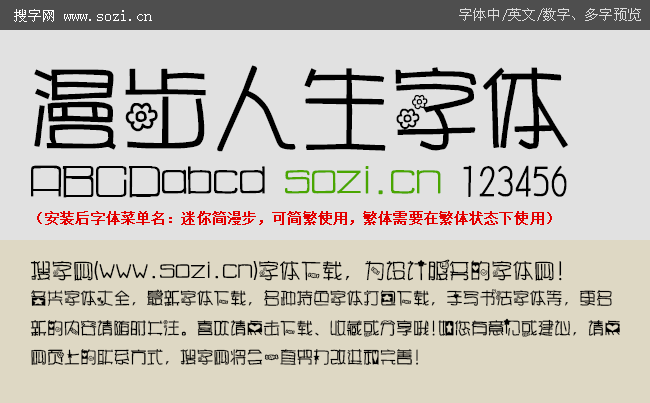
漫步人生字體
搜字網(wǎng)給大家提供一款漫步人生字體手機(jī)中文字體下載。這款手機(jī)中文字體以迷你簡漫步體為原形,在字體筆畫間加上了可愛的卡通花朵圖形,漫步體是一款POP字體,筆畫平直、粗細(xì)一致、結(jié)體飽滿、連貫方正,加入花朵之后增強(qiáng)了趣味性,非常適合喜歡個(gè)性的朋友在手機(jī)上安裝使用。